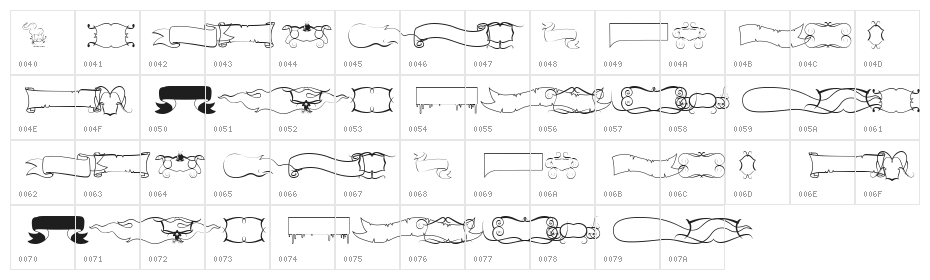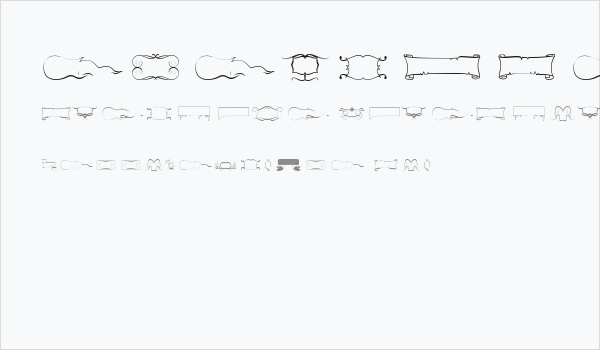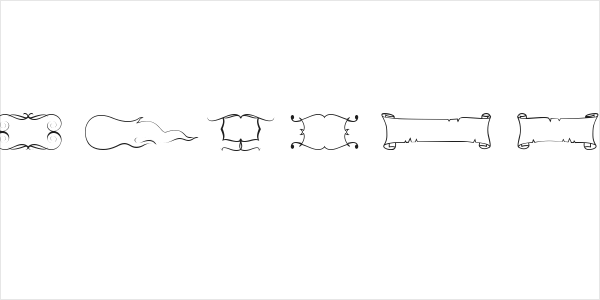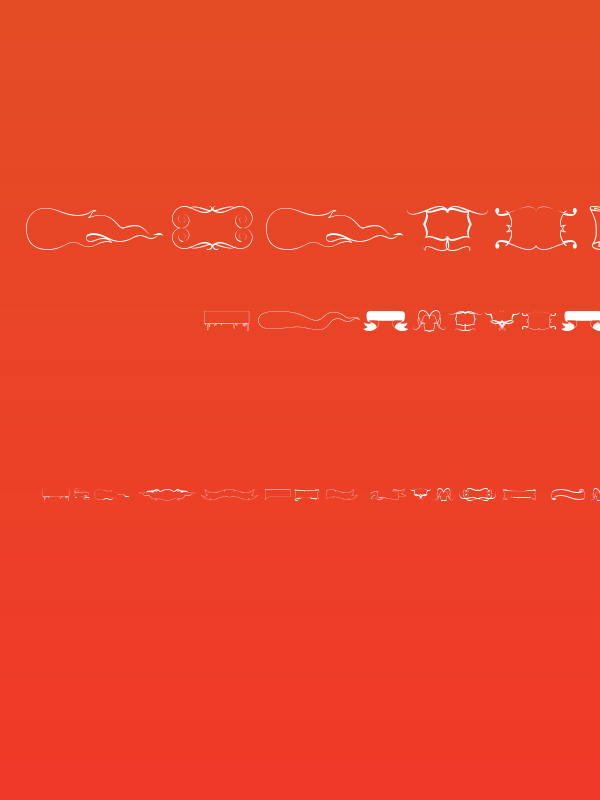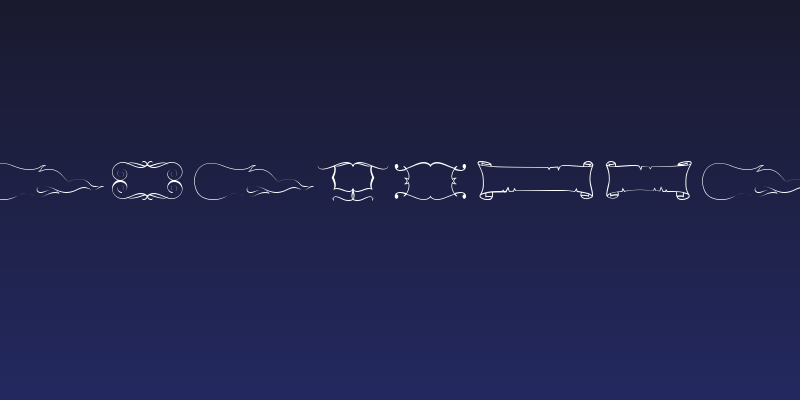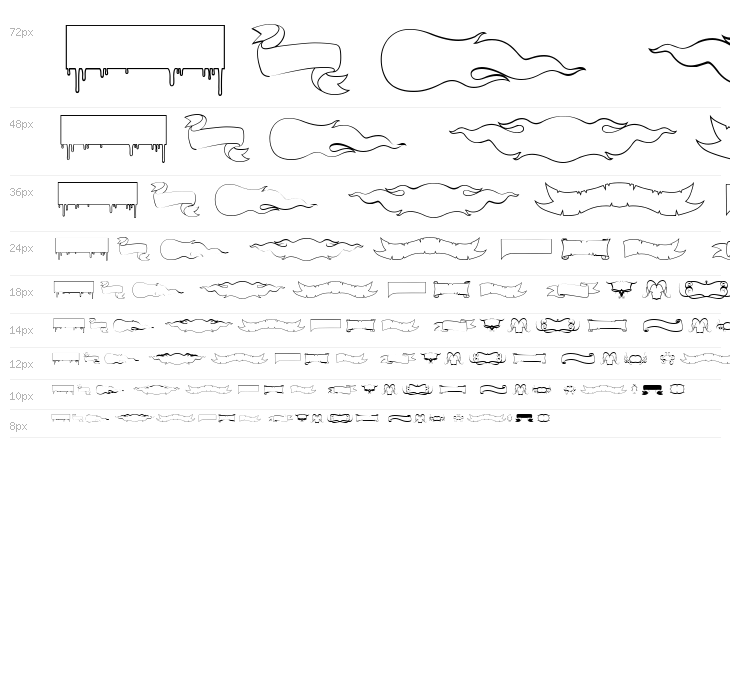
Elegance Font
| 使用场景 | Design embellishments, borders, frames. |
| 推荐项目 | These decorative elements could be used in graphic design projects, such as creating borders, frames, or embellishments for invitations, posters, or digital artwork. |